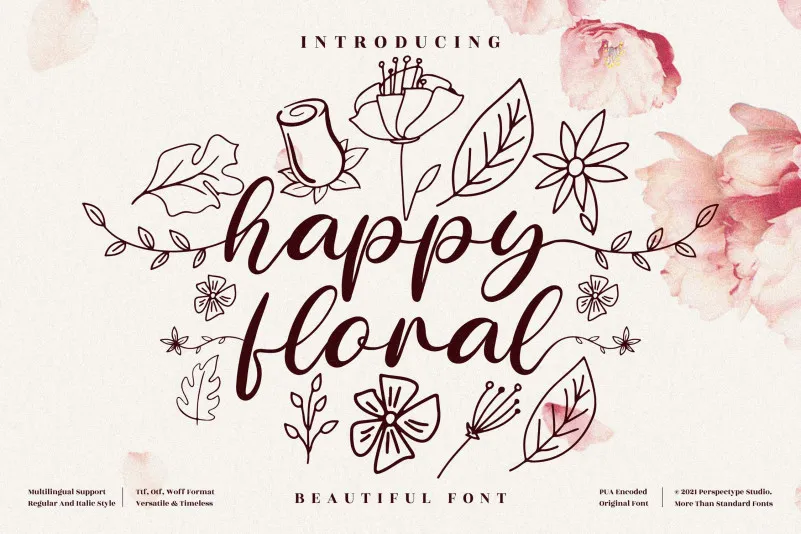
Happy Floral Font – Download Grátis
A fonte “Happy Floral Font” é uma criação da perspectype, perfeita para aqueles que buscam um toque sofisticado e encantador em seus projetos design. Desenvolvida como um script leve e agradável ao olhar, essa fonte traz uma sensação única e um impacto surpreendente. Ela adorna qualquer projeto de forma elegante e refinada. Com seu PUA (Propriedades Unicode Associadas) codificado, é simplesmente incrível o número de caracteres únicos e ligaturas que você pode acessar com facilidade. É uma escolha perfeita para designers que desejam dar um toque luxuoso a qualquer arte ou design que estão criando. Perfumada por flores coloridas e ornamental, essa fonte é ideal para anúncios de moda, embalagens, revistas de decoração, ou mesmo como uma maneira elegante de adicionar o bom gosto ao seu logotipo. Sem dúvidas, “Happy Floral Font” irá transformar qualquer projeto em algo que chama a atenção.